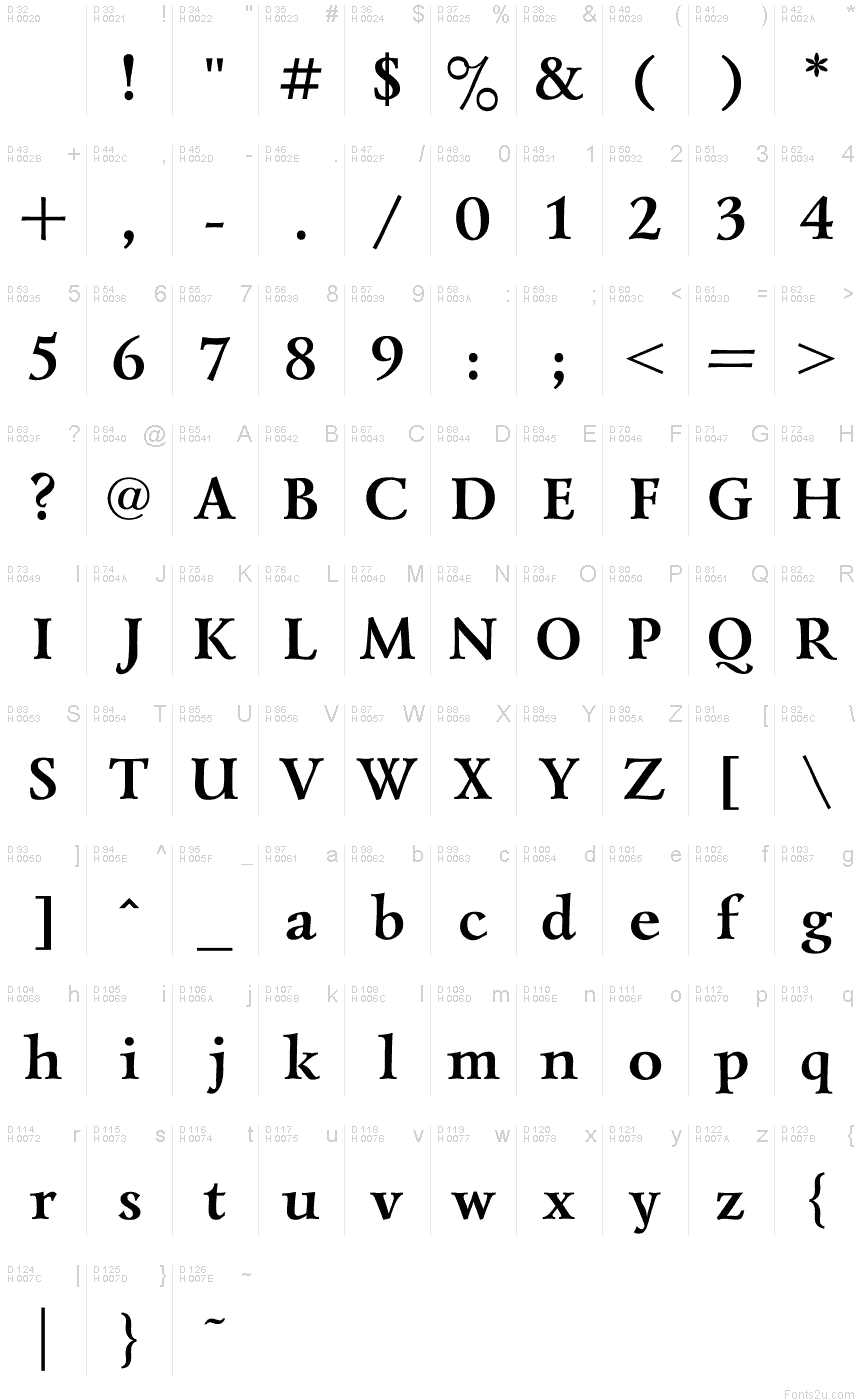
Lazurski Bold
Lazurski Bold od Atech Software to darmowy szeryfowy krój pisma w stylu kaligraficznym, który przywodzi na myśl literacki klimat minionych epok. Litery łączą szerokie, wyraziste szeryfy z płynnymi krzywiznami i ostrymi zakończeniami, dzięki czemu całość wydaje się formalna, ale nie sztywna.
Dzięki temu ten darmowy font naturalnie sprawdza się na okładkach książek, winietach czasopism, plakatach w stylu vintage, etykietach win czy produktów aptecznych oraz w napisach teatralnych. Świetnie nadaje się również do krótkich nagłówków, inicjałów i monogramów, gdzie zamaszyste krzywe i zwężające się detale nadają tekstowi uroczysty charakter, nie stając się przy tym przesadnie ozdobnym.